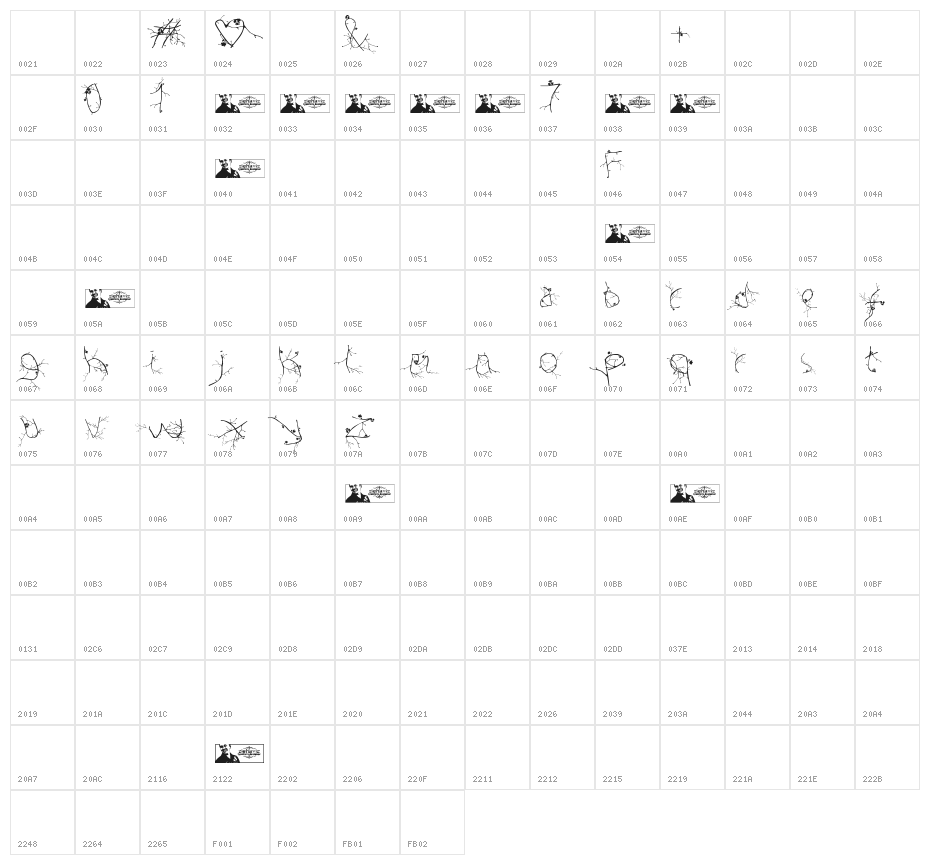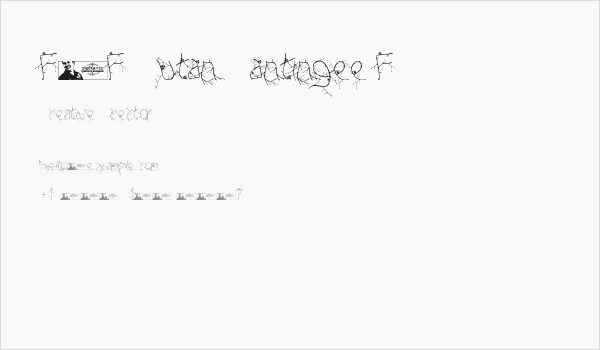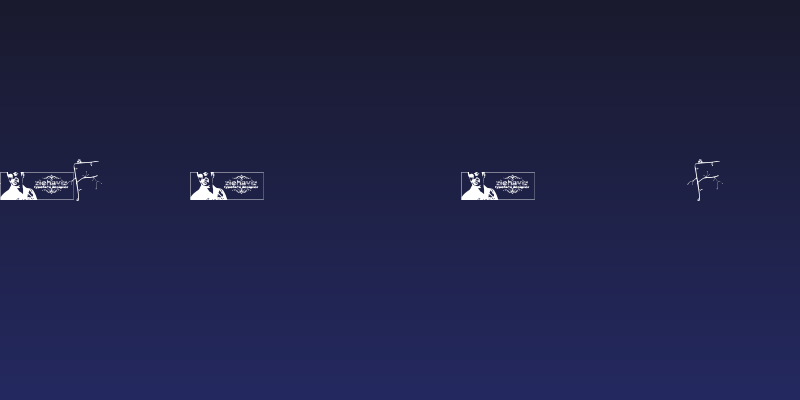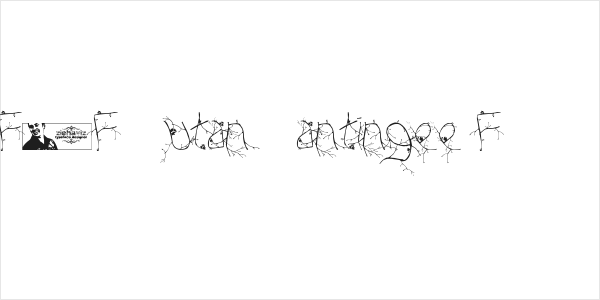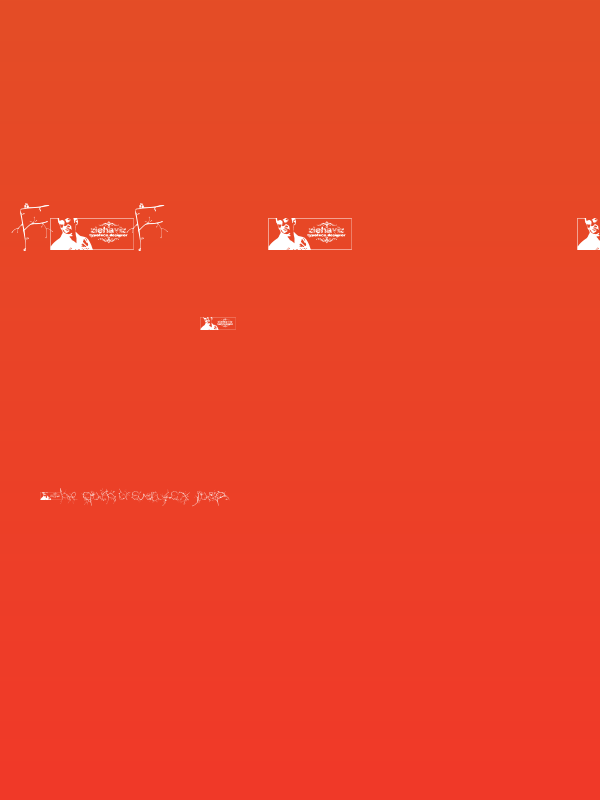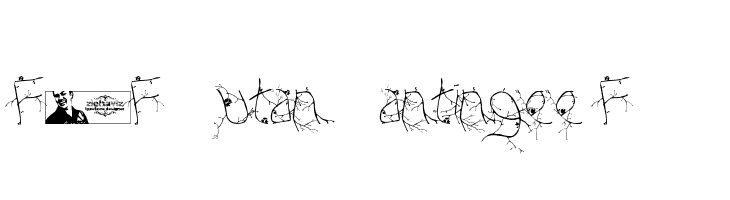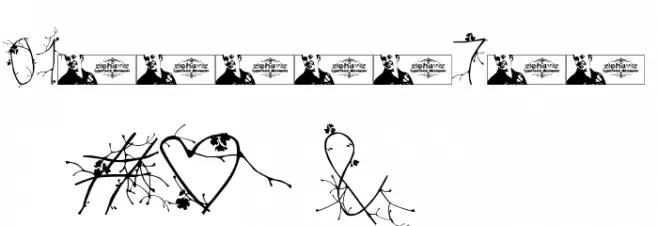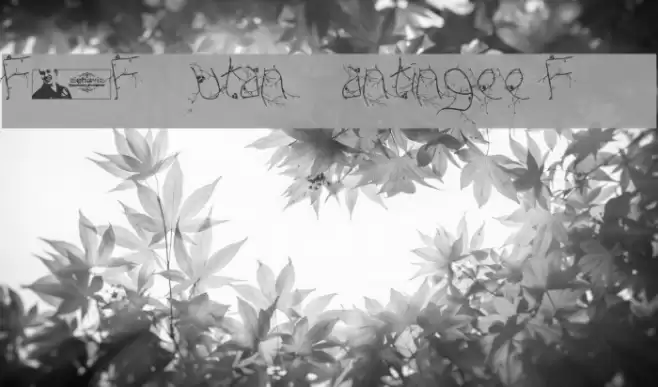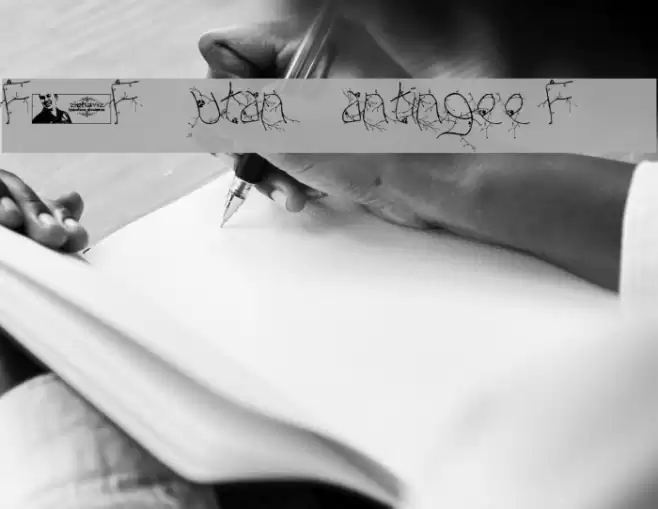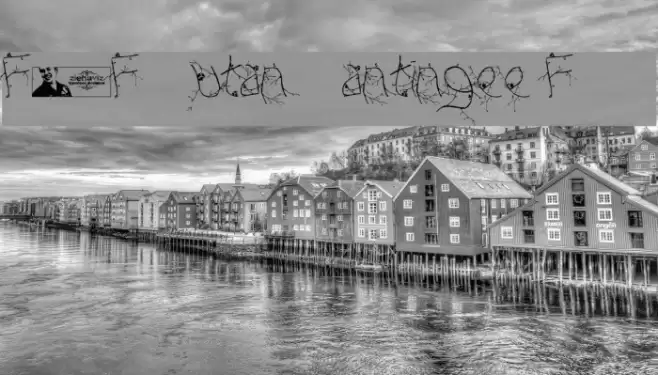
FTF Hutan Rantingee FREE Font
✎ Decorative
| Caso de uso | Logos, Headlines, Artistic projects |
| Proyectos propuestos | Ideal for eco-friendly branding, nature-themed event invitations, artistic posters, and creative projects that seek a natural and organic look. |